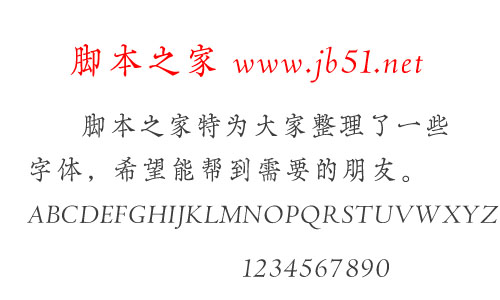
方正志安體字體是日本首次登陸的一款元朝體,是一款組合字體,漢字部分源自元代福建刊本《分類補注李太白詩》的“志安體”,西文部分為「K.E.Libra」,組合成為具有現(xiàn)代感的綜合書體,歡迎需要方正志安體的朋友前來下載使用。
方正志安體,宋代福建地區(qū)的出版社中大眾熟知的是余仁仲的“萬卷堂”,不過到了元代,余志安的“勤有書堂”變得更加有名。